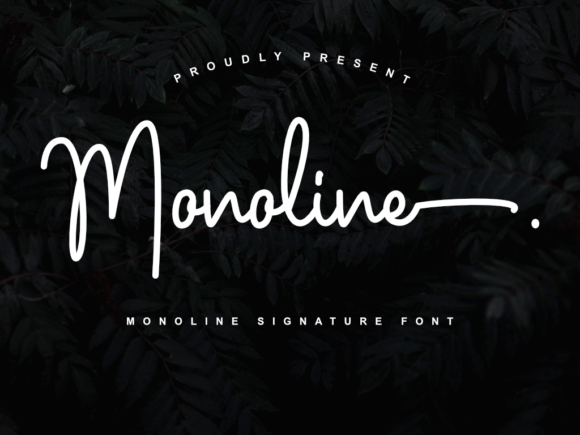
Monoline
Mencari elemen desain yang tepat bisa jadi sulit, namun Monoline menawarkan koleksi luar biasa yang akan langsung meningkatkan kualitas karya Anda.